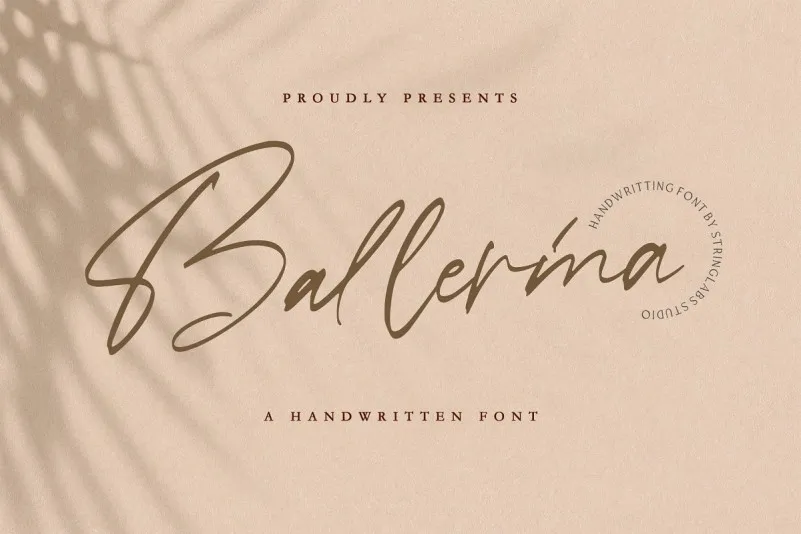
Ballerina Script Font é uma elegante tipografia feita à mão que traz estilo inconfundível. Esta criação do designer Hamilton adiciona sofisticação e modernidade a qualquer projeto de design, seja ele para marcas de moda, convites de casamento, cartões de negócios, logotipos, assinaturas ou até mesmo escritura artesanal. Com sua natureza única e conceito inovador, essa fonte perfeita atende uma variedade de aplicações visuais. Perfeito para quem busca um elemento distintivo em suas criações, esta Ballerina Script Font não apenas enriquece o design com seu traço elegante, mas também oferece elementos criativos e cool que garantirão uma impressão única. Sem dúvida, ela é uma escolha ideal para aqueles procurando por um toque especial em seus projetos.